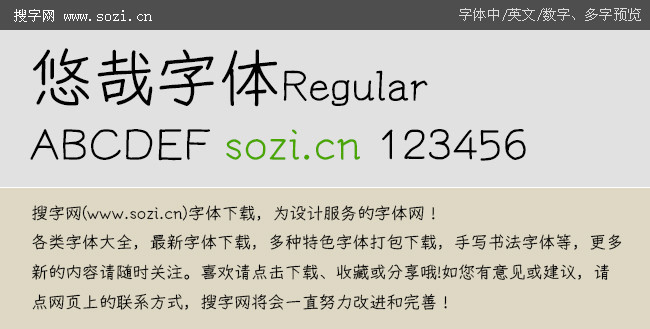
悠哉字體Regular
搜字網(wǎng)提供一款悠哉字體Regular中文藝術(shù)字體下載,悠哉字體是一款手寫風(fēng)格的字體。目前已補(bǔ)全原字體中有對(duì)應(yīng)繁體字的簡(jiǎn)體字,并補(bǔ)全了4808常用繁體中文漢字,以及3500常用簡(jiǎn)體中文漢字。適合卡通風(fēng)格海報(bào)、兒童包裝等廣告設(shè)計(jì)。